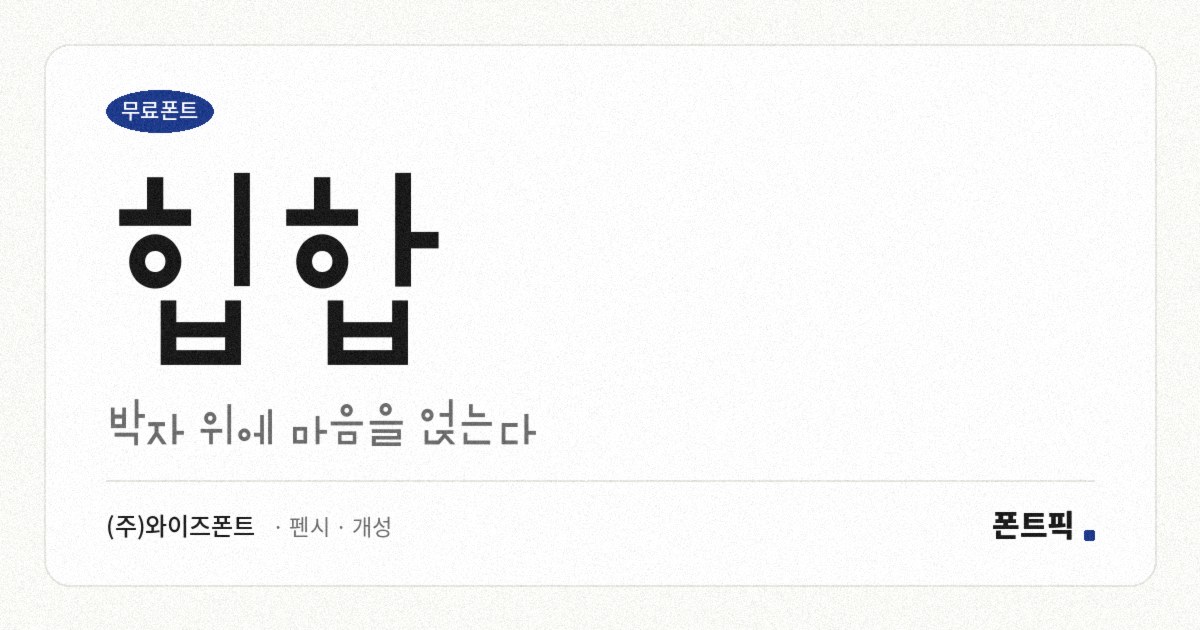
힙합 서체 견본
힙합
TDTDHiphop
• 굵기1종 Regular
• 글자 수완성형 11,172자
• 분류펜시 · 개성
힙합 소개
와이즈폰트의 손글씨 서체입니다. 한글과 로마자의 성격이 뚜렷하게 갈리는 것이 이 서체의 특징입니다.
한글은 펜으로 빠르게 쓴 듯한 손글씨입니다. 받침이 붙을 때 글자가 0.28em 아래로 내려가는 탈네모틀이라 글줄이 리듬을 타고 오르내리고, 낱자는 가로로 퍼져 있습니다. 반면 영문과 숫자는 획을 각지게 깎아 놓아서 인상이 확 달라집니다. 같은 문장 안에 한글과 로마자를 섞으면 그 대비가 그대로 드러납니다.
그래서 쓰는 자리도 갈립니다. 한글만 쓰면 무난한 손글씨체이고, 로마자를 섞으면 거친 느낌이 살아납니다. 어느 쪽이든 한두 어절짜리 제목용입니다. 현대 한글 11,172자를 모두 담았고 굵기는 하나입니다.